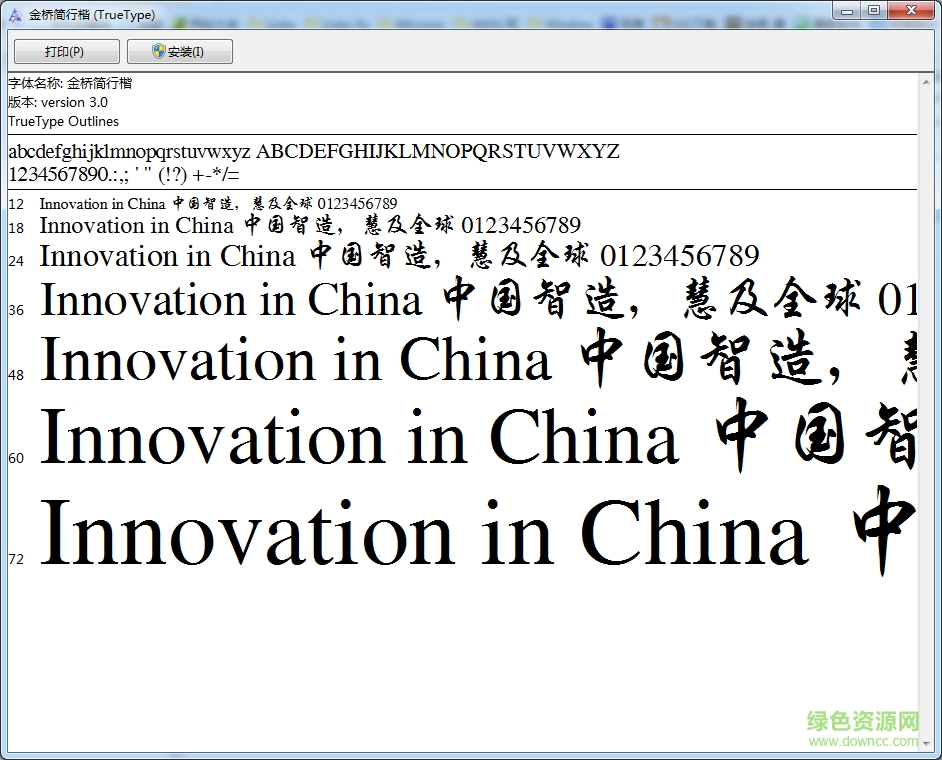
jqxingkaijt字体也就是金桥简行楷字体,这款字体笔画洒脱,笔锋细腻,完美阐释了行楷酷炫风格,深受广大书法家喜爱,适应于排版设计、广告创意、印刷等领域,需要的朋友欢迎来绿色资源网免费下载使用。
jqxingkaijt字体介绍
jqxingkaijt字体是一款常用的行楷字体,这款字体融合了行楷两大字体的元素,展现出一种行书的凌厉,很具观赏感性,字体飘逸洒脱,行笔流畅自然,喜欢这款字体的朋友欢迎来绿色资源网下载体验!